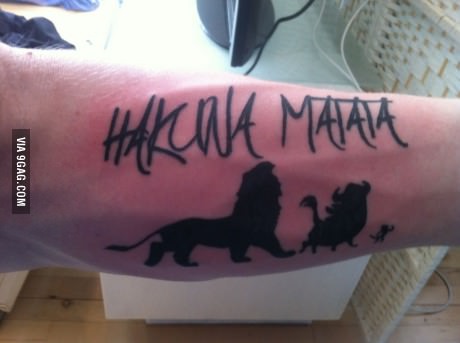
Font gesucht: Tattoo
ich bin auf der Suche nach der Schriftart des angehängten Bildes.
Bin auf das Bild vor längerer Zeit gestoßen und würde mir daraus gerne eine Vorlage für ein eigenes Tattoo schaffen.
ich hab mal kurz gesucht, aber nix dergleichen gefunden, was aber nicht heissen soll das es kein font ist. bist du dir sicher, dass du dir diesen script font tätowieren lassen willst? wieso einen fertigen font? da gibt es doch echt bessere möglichkeiten das ganze individueller zu zeichnen. z.b. hier und hier oder hier.
hier noch ein paar alternative fonts: